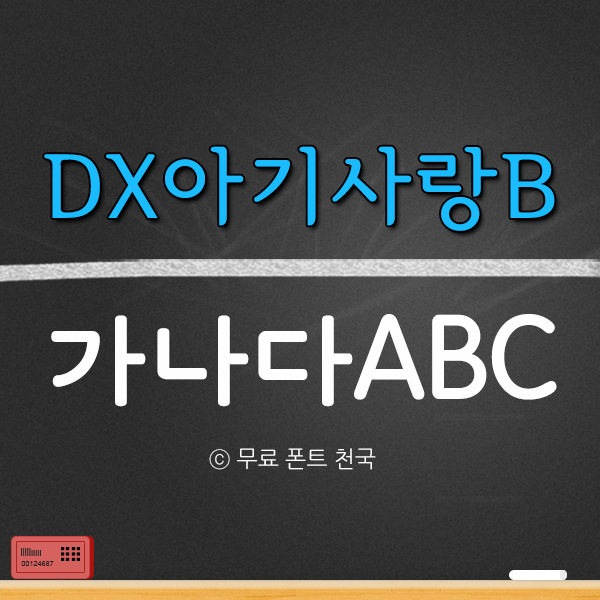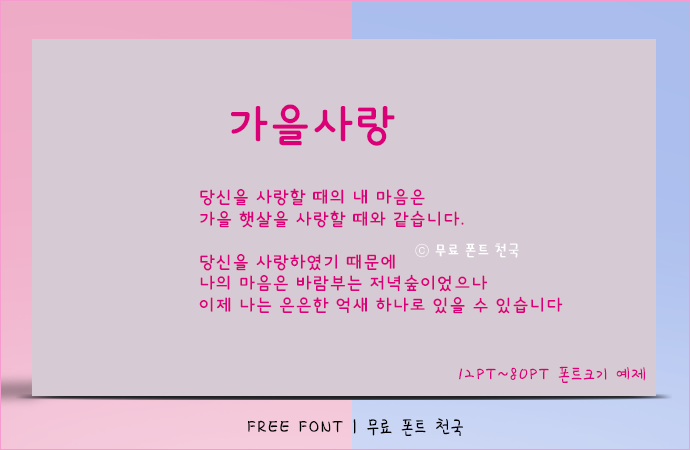
좋은 가독성과 굵은 서체, DX아기사랑B 폰트
굵고 단단한 느낌을 서체로 표현한 DX아기사랑B 폰트입니다. 출판물과 영상물에서 글자의 크기가 잘 표현되도록 최적화 시켜 제작한 서체입니다. 개인에게는 무료로 사용 가능하지만 기업과 공공기관에서는 라이센스를 구매해서 사용하셔야 하는 제한적 무료 폰트입니다. 무료 폰트 천국에서 제공하는 폰트 사용 범위, 저작권 정보는 최신 정보가 아닐 수 있으며 폰트 사용과 관련된 자세한 사항 및 사용 정보는 아래 게시된 '폰트 소유권' 홈페이지를 참고하시면 됩니다. TTF 파일은 폰트 폴더에 복사해서 사용하셔야 하며, EXE로 된 설치 배포형 폰트의 경우 설치를 하시면 폰트가 자동 적용됩니다.
DX아기사랑B 폰트 # 미리보기
12~80PT 크기로 가독성을 테스트 해본 DX아기사랑B 폰트
100PT 크기 이상으로 작업한 오버레이 효과를 적용한 DX아기사랑B 폰트
100PT 크기 이상으로 그레이언트를 효과를 적용한 DX아기사랑B 폰트